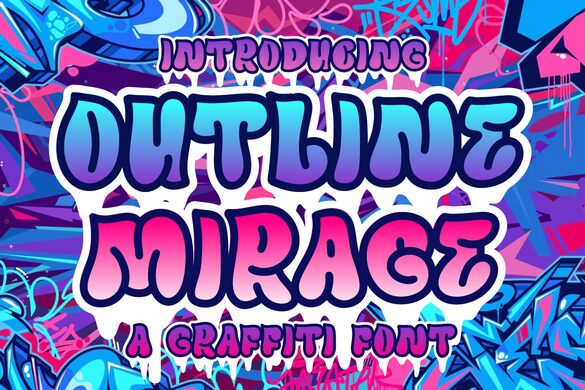
Outline Mirage Fill
Shanaf Studioによる「Outline Mirage Fill」は、柔らかく膨らんだシルエットと、描かれたというよりも流し込まれたかのような重厚な黒の塗りつぶしが特徴の無料グラフィティフォントです。丸みを帯びた曲線、どっしりとしたプロポーション、引き締まった接合部が、アルファベット全体に遊び心とストリート感、そして少しのシュールさを漂わせるムラルのようなエネルギーを与えています。
ポスターのタイトル、音楽のアートワーク、若者向けのブランディング、ステッカーデザイン、タイトルカードなどに最適で、このスプレー缶のような力強い雰囲気を持つ無料フォントは、形状だけでメッセージを伝えることができます。ウェットで膨張したような手書き感を出したい時に、特に短い言葉やカバーデザイン、ロゴ風のロゴタイプとして活用してみてください。